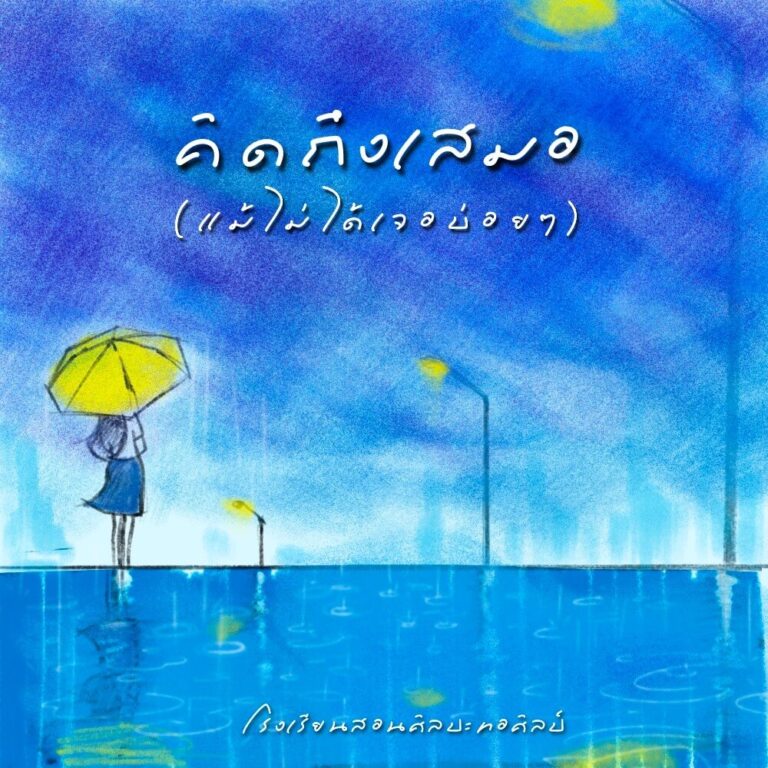
ฟอนต์ torsilp-gimchi (อ่านว่า ทอศิลป์-กิมจิ) เป็นตัวอักษรไทยในรูปแบบตัวอักษรเกาหลีอีกตัวหนึ่ง ได้แรงบันดาลใจจากรูปแบบตัวอักษรที่มีเอกลักษณ์ของเกาหลี และกระแสที่ไหลบ่าของวัฒนธรรมประเทศเกาหลี ที่กระจายครอบคลุมไปแทบจะทั่วทั้งโลก มากมายจนกระทั่งบางเวลาก็เผลอคิดไปเองว่า ยุคสมัยนี้เป็นยุคสมัยของเกาหลีเสียแน่แล้ว
ฟอนต์ torsilp-gimchi ไม่เหมาะสำหรับเอาไปทำเป็นตัวพื้นนะครับ
torsilp-gimchi